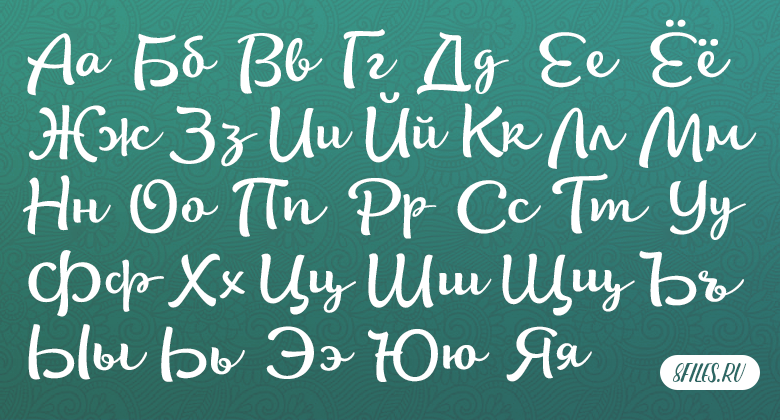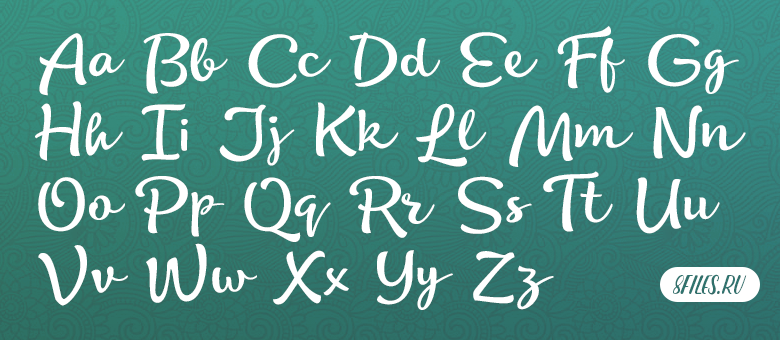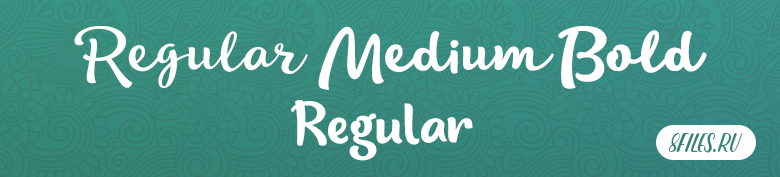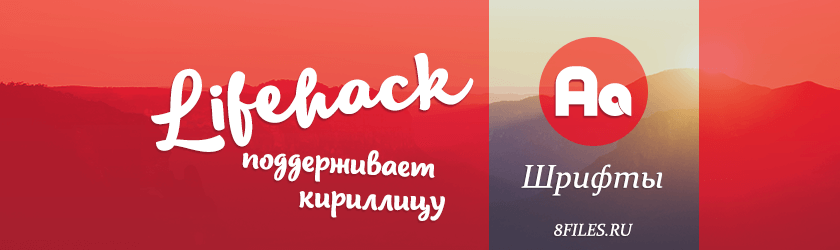
Font (шрифт) Lifehack
. Представляю вашему вниманию красивый шрифт: Lifehack. Шрифт прекрасно подойдёт для творческих людей. Есть схожесть с популярным шрифтом - Лобстер, на мой взгляд даже лучше его. Надеюсь он вам пригодится
Поддерживает Кириллицу
И само собой Латиницу
Имеет 8 стилей: от среднего и до толстого + один без засечек. И дублирующие наклонные.